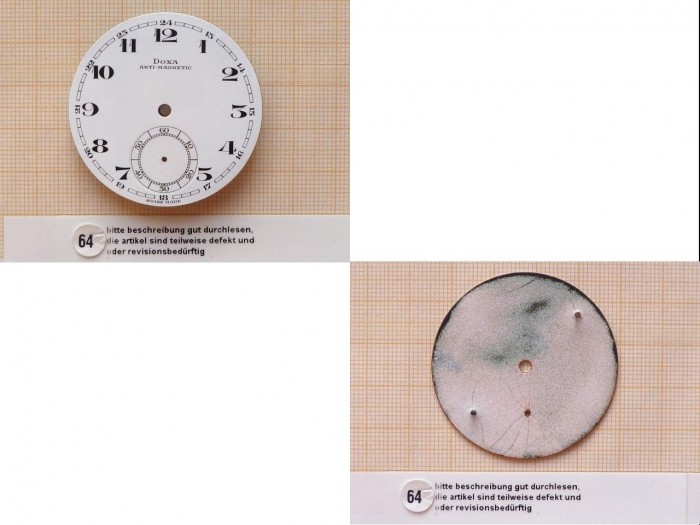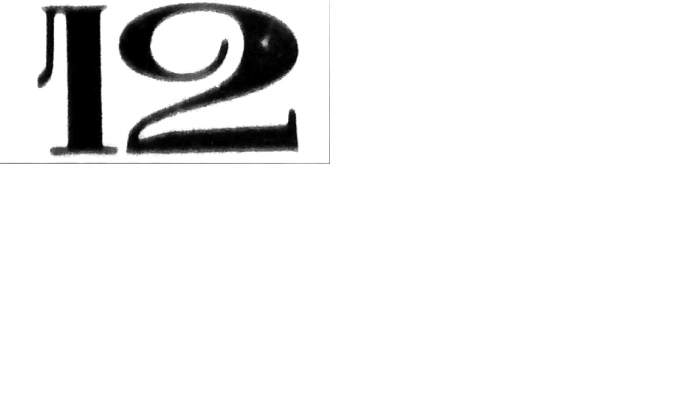
Kennt jemand diese Schrift? (Longines Olympic)
kennt jemand von euch diese Schrift? Es ist die 12 von einem Uhrzifferblatt. Vielen Dank für eure Expertise!
ich habe diese Schrift auch auf einem alten Taschenuhrzifferblatt gefunden - also keine Eigenkreation von Longines, sondern vermutlich früher recht verbreitet. Kennt jemand diese oder eine ähnliche Schrift?
Das muss aber dann trotzdem nicht bedeuten, dass es dann auch eine benannte Schift gibt. Gut Möglich, dass schicht ein Schweizer Uhrenhersteller einfach vom Ziffgerblatt eines anderen Uhrenherstellers die Ziffern übernommen hat, oder gar beide die Zifferblätter von gleichen Zulieferer beziehen. Soch eine Verflechtung ist ja durchaus üblich. Da stellt eine Fima Saphilager her, eine andere die winzigen Schrauben, eine Dritte stellt nur Zeiger her und eine weitere die Federn für den Aufzug und für die Unruh - und eben auch wieder ein Spezialist nur Zifferblätter. Das ist ja auch die Ursache, dass bestimmte Produkte oft räumlich so eng beieinander poduzieren.